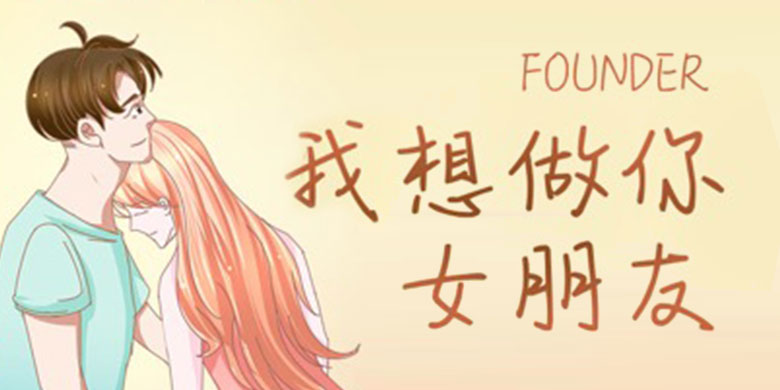
品牌:方正手迹设计师:刘晔发行时间:2019字库编码:大陆简体(GB2312-80)分类:常规书写·硬笔字体属性:精品字
结构灵活,粗细变化不大,书写流畅,笔画柔和,文艺清新,给人留下温婉别致的印象。适用于文艺类的书刊、品牌广告和产品包装设计,以及社交网络的个性化用字。
品牌:方正手迹设计师:刘晔发行时间:2019字库编码:大陆简体(GB2312-80)分类:常规书写·硬笔字体属性:精品字
结构灵活,粗细变化不大,书写流畅,笔画柔和,文艺清新,给人留下温婉别致的印象。适用于文艺类的书刊、品牌广告和产品包装设计,以及社交网络的个性化用字。